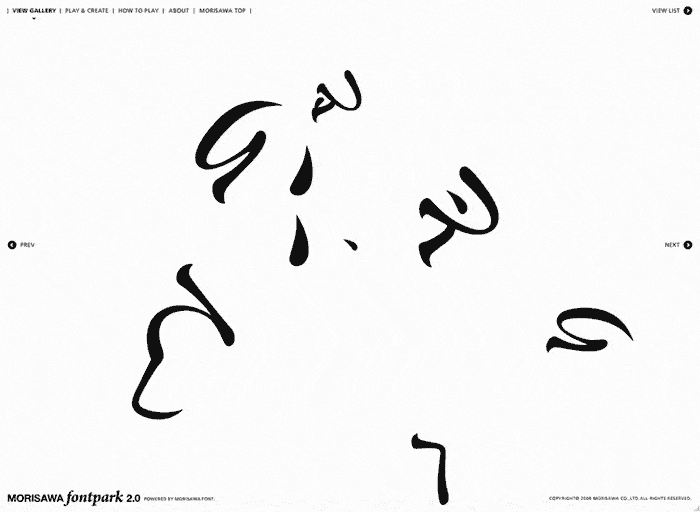
FontPark, le dessin par la typo… c’est par cette entrée que j’ai découvert ce site interactif, entièrement réalisée avec Flash où chacun peut s’essayer à une composition personnelle en usant des formes calligraphiques chinoises de Morisawa. Vous dessinez, vous enregistrez et on peut ensuite replay à l’infini votre création tout en notant ceux des autres participants. C’est ingénieux et fluide comme le dit si bien le web-blogueur de X-Prime et j’ajouterai enfin que 90% des dessins tournent autour du visage imaginaire de chacun. L’imago de Jung n’est pas loin. Typographie et anthropomorphisme n’ont jamais fait aussi bien ménage :-). Allez! à vos souris!